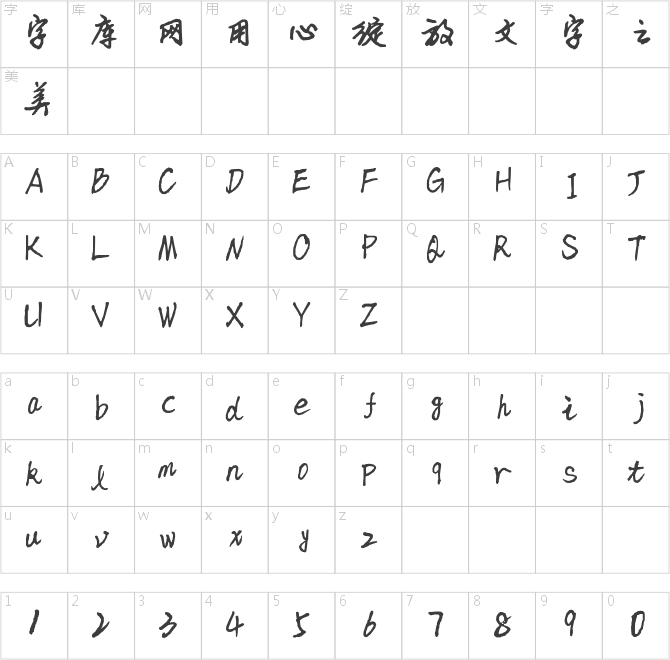
字体名称: 张勃钢笔体
张勃钢笔体
张勃钢笔体是以行楷的体势为基调,区别于传统的书法字体,更为注重线条的粗细变化,字体柔中带刚,从而丰富字形的节奏感使字体更具艺术感和手原笔手写痕迹,更贴近于真实感官享受
张勃钢笔体字体字库是一款让人赏心悦目、百看不厌的中文字体,适合各类广告和产品包装设计应用,字体大小3.68MB,格式为ttf字体,上传用户是得·岸,作者/版权方为张勃